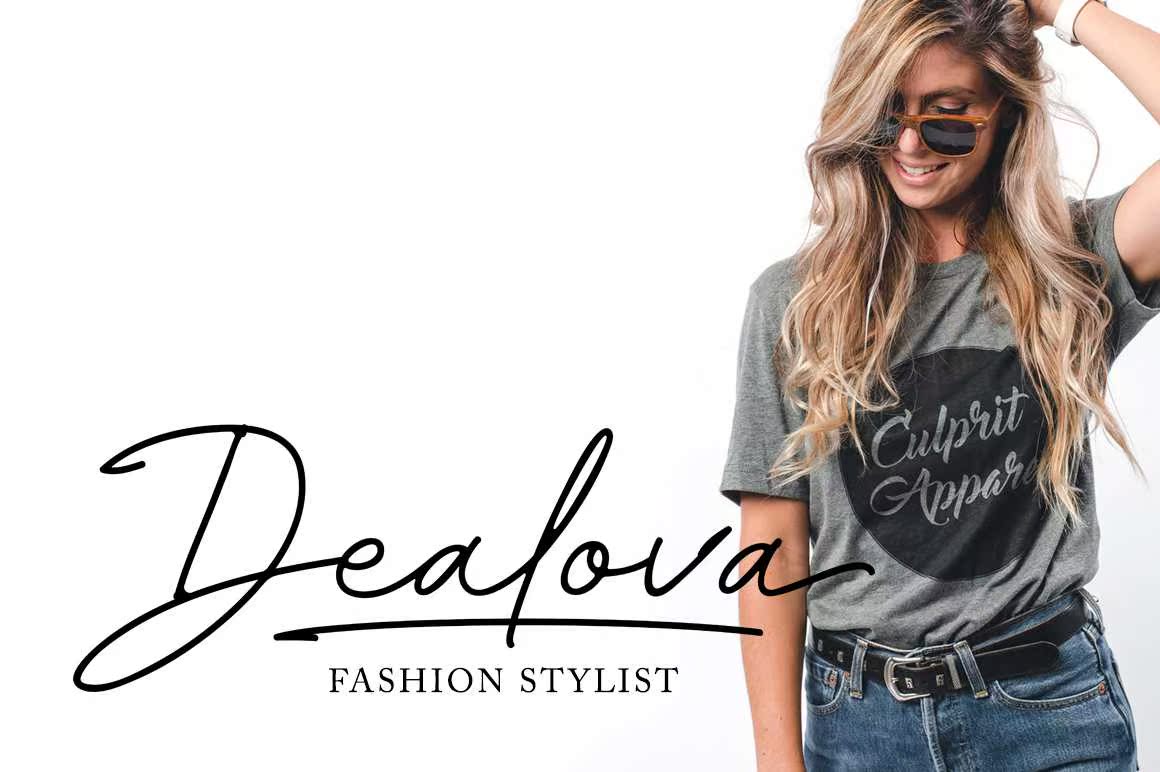
介绍Elocity,Astylish Handright Tensignature for。速度是指他最喜欢的广告、包装、婚礼宣传、社交媒体、广告和水线摄影。介绍Elocity,Astylish Handright Tensignature for。速度是指他最喜欢的广告、包装、婚礼宣传和水线摄影。介绍Elocity,Astylish Handright Tensignature for。速度是指他最喜欢的广告和水线宣传,社会媒体、广告和水印摄影。